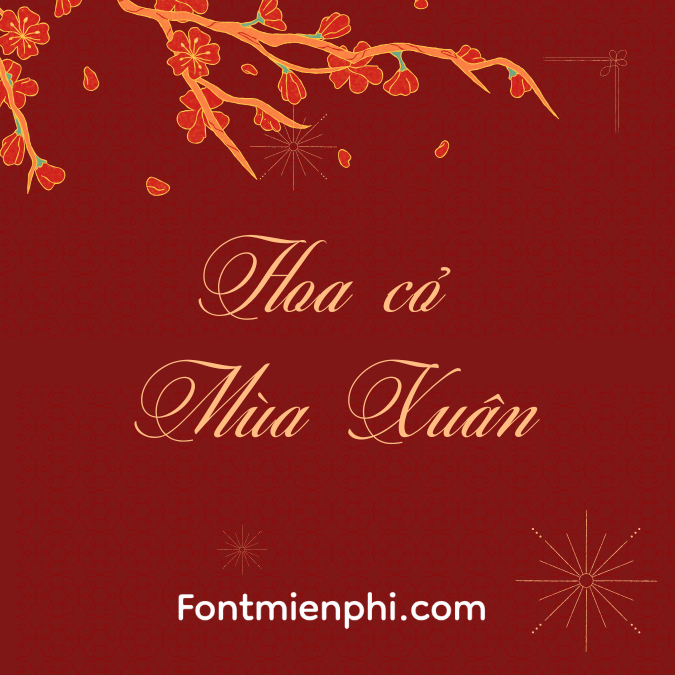
Font Việt hóa 1FTV VIP Thei , Font Việt hóa tết
**Font Việt Hóa 1FTV VIP Thei – Nét Chữ Đẹp Chuẩn SEO Cho Mùa Tết**
Font Việt hóa **1FTV VIP Thei** là bộ font chữ độc đáo, được thiết kế tinh tế dành riêng cho dịp Tết, giúp các sản phẩm thiết kế trở nên bắt mắt và ấn tượng hơn. Với phong cách viết tay nghệ thuật kết hợp nét thanh đậm cân đối, font chữ này phù hợp cho poster, thiệp chúc mừng, banner quảng cáo, hay các ấn phẩm truyền thông mùa lễ hội.
### **Đặc điểm nổi bật của Font 1FTV VIP Thei**
✔ **Thiết kế Việt hóa chuẩn**: Hỗ trợ đầy đủ dấu tiếng Việt, đảm bảo tính thẩm mỹ và dễ đọc.
✔ **Phong cách Tết độc đáo**: Nét chữ uốn lượn, sáng tạo, mang đậm không khí xuân với hoạ tiết truyền thống.
### **Ứng dụng font 1FTV VIP Thei**
– **Thiết kế in ấn**: Thiệp Tết, lịch, bao lì xì, standee cửa hàng.
– **Truyền thông số**: Banner website, bài đăng MXH, video chúc Tết.
– **Quảng cáo thương hiệu**: Tạo điểm nhấn cho slogan, logo dịp đầu năm.
Font Việt hóa 1FTV VIP Thei – Font Việt hóa tết Font phù hợp với các thiết kế ấn phẩm quảng cáo vào dịp tết. Font đã được Việt hóa đầy đủ nhưng không có bộ chữ số